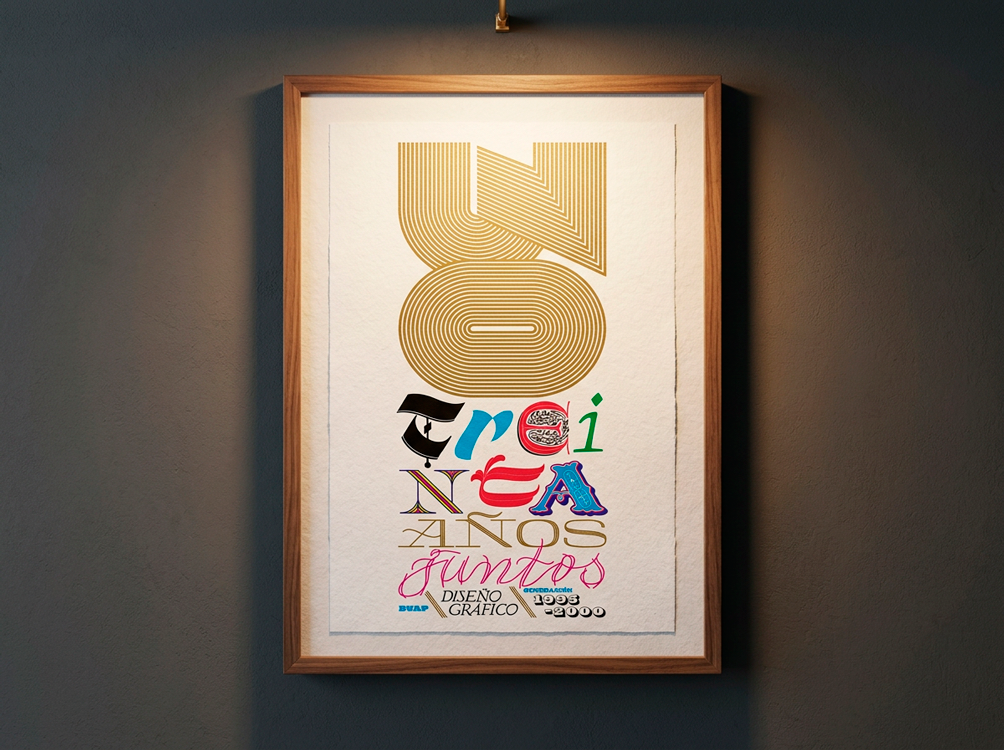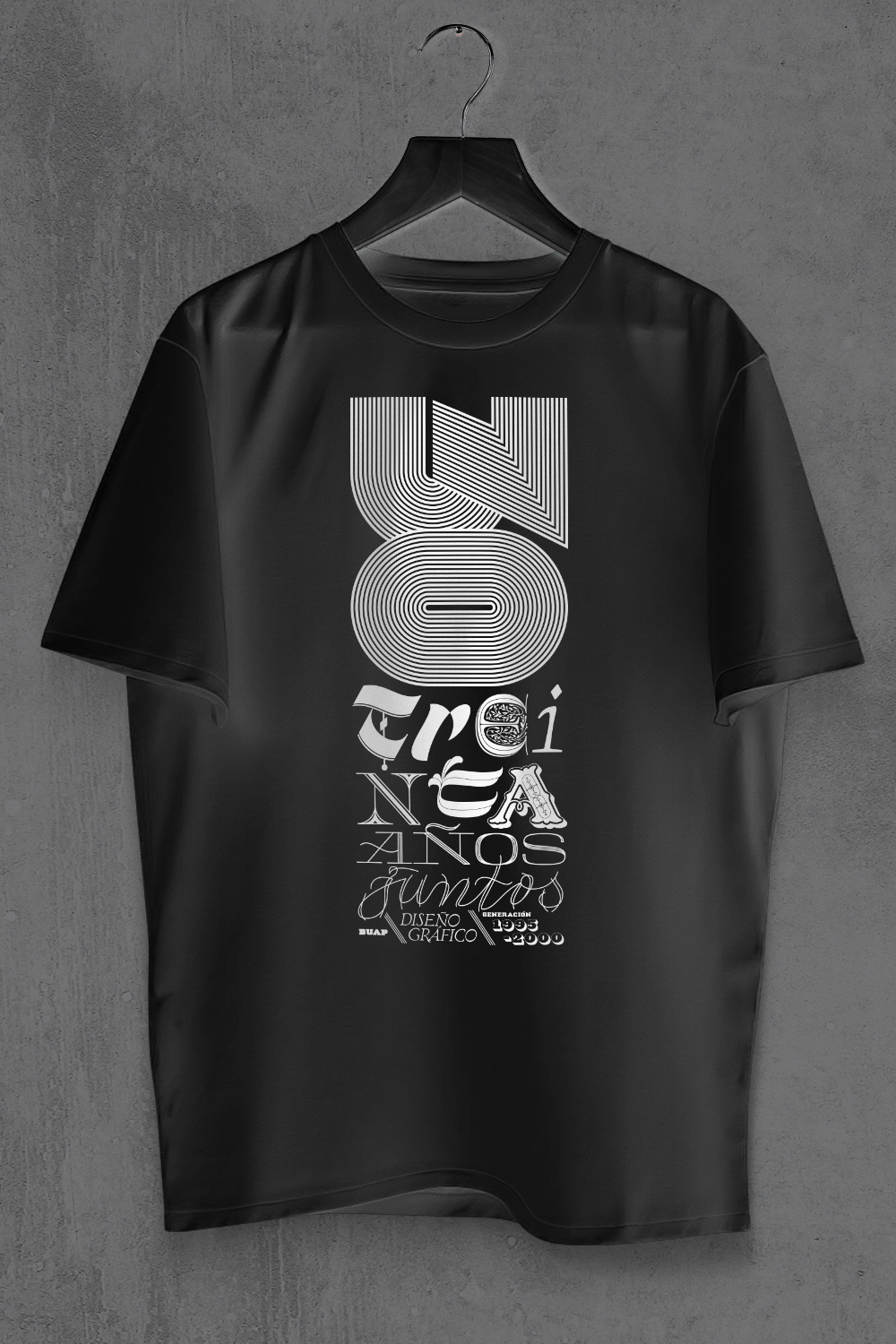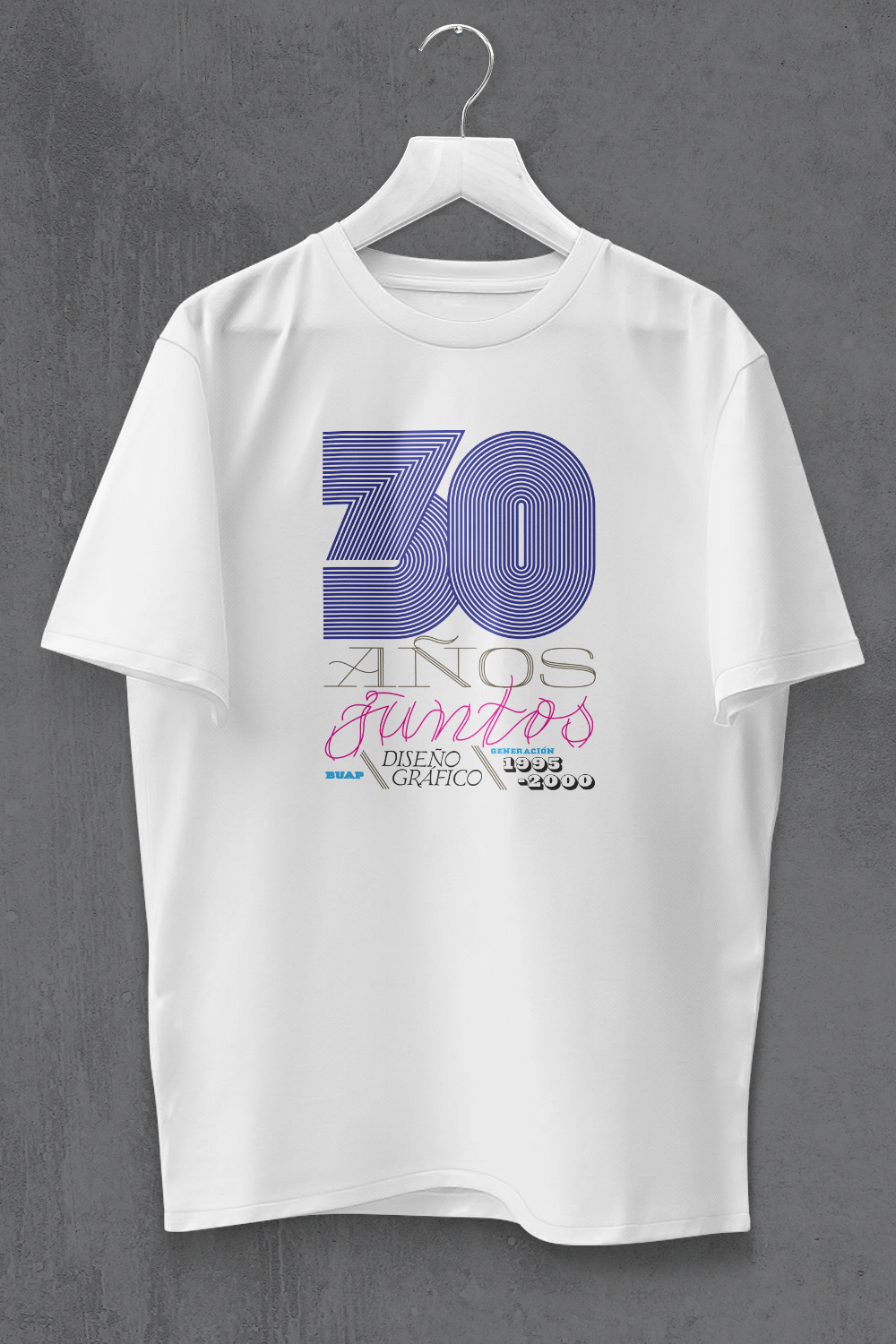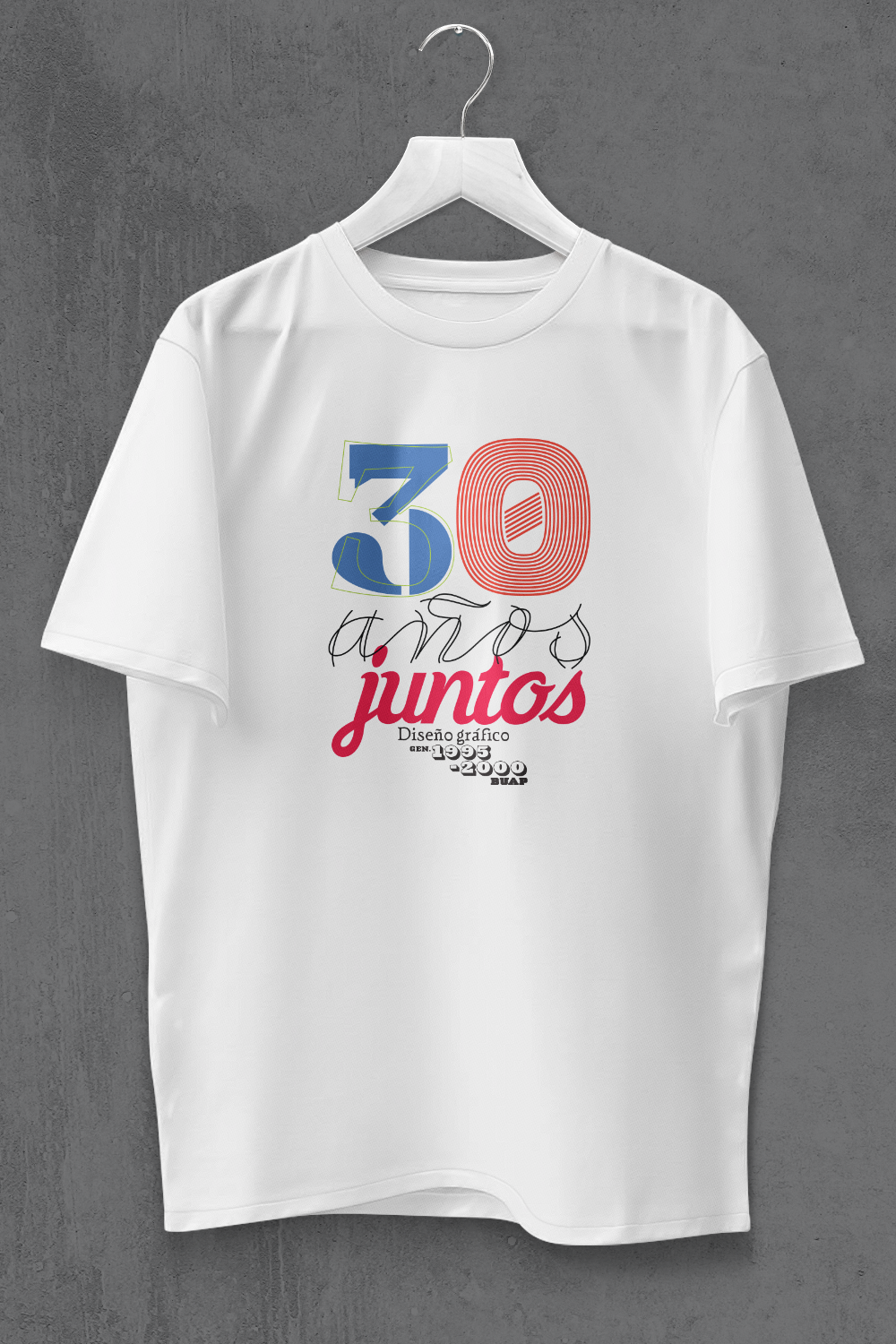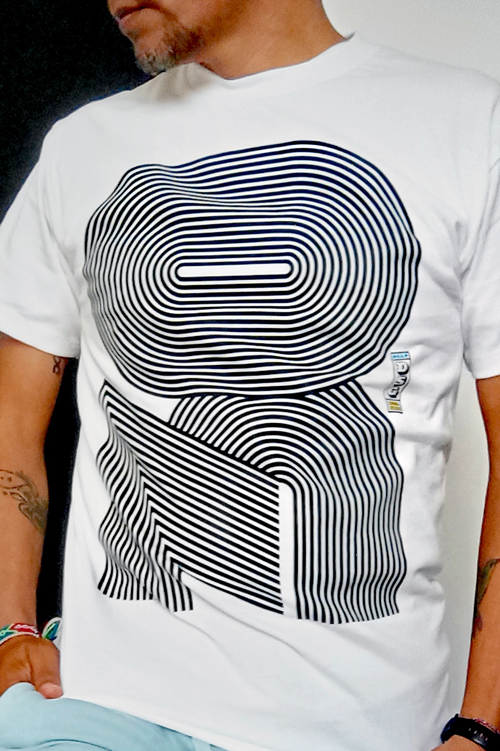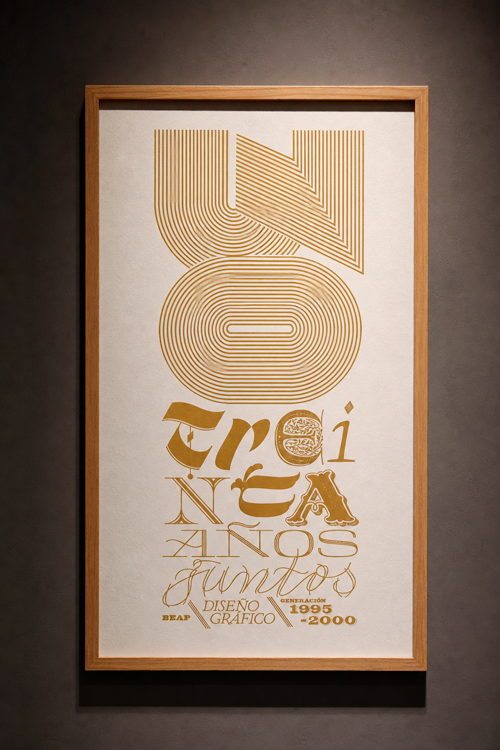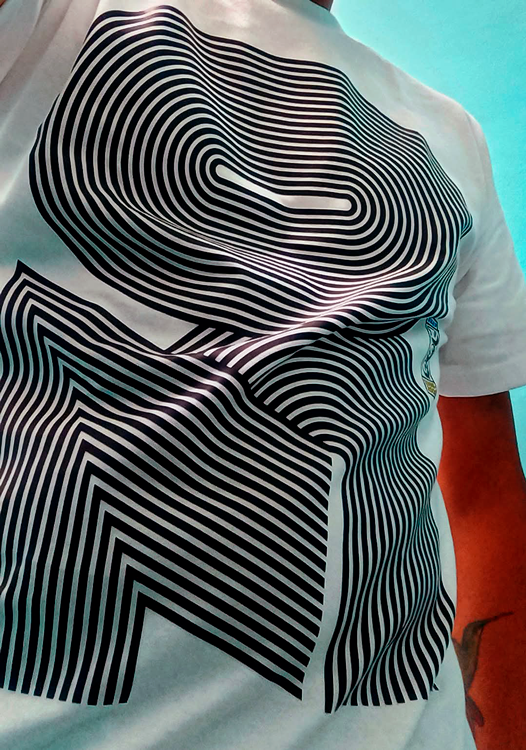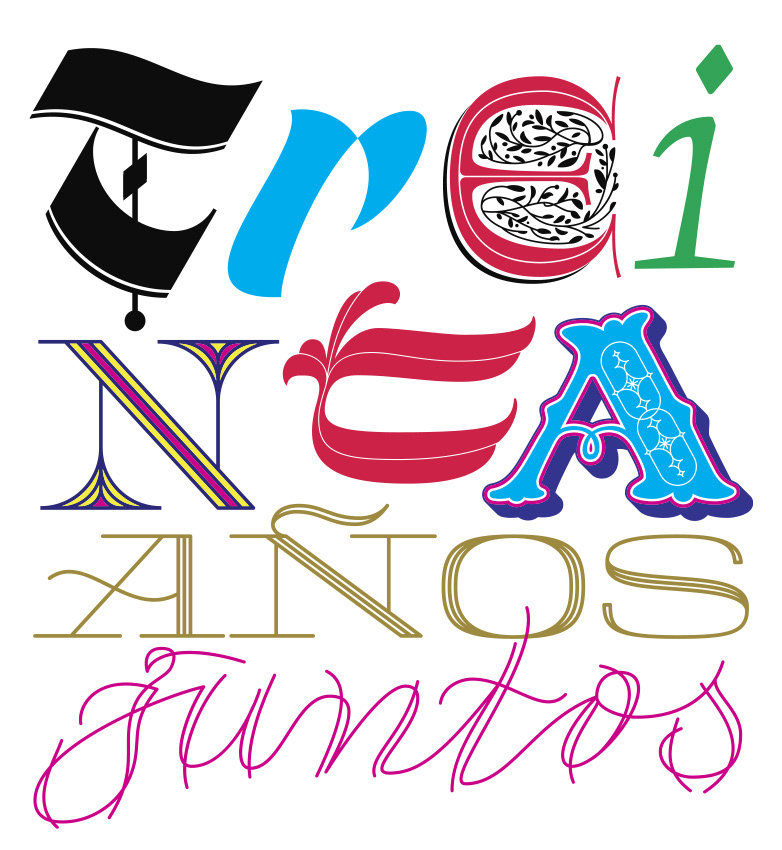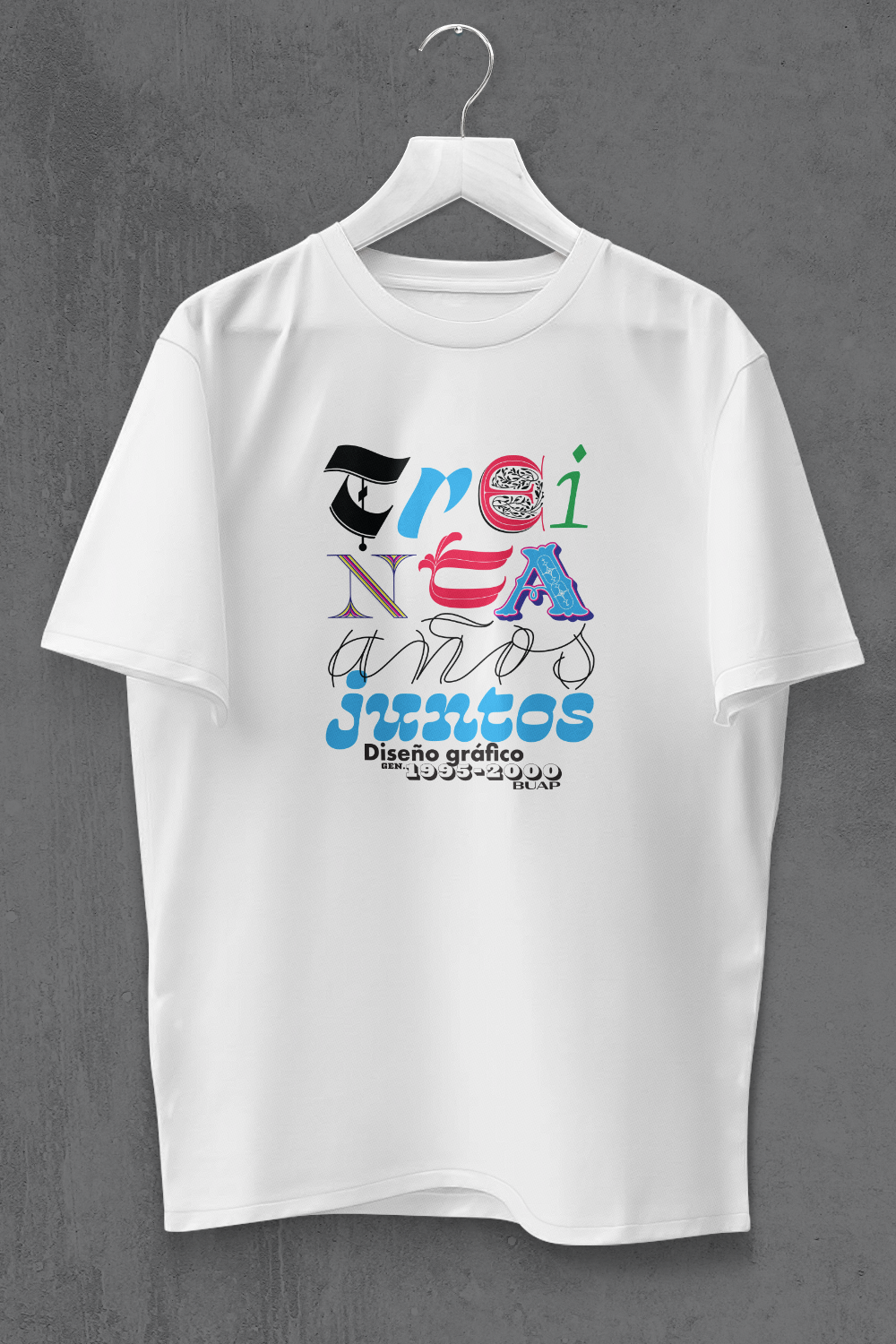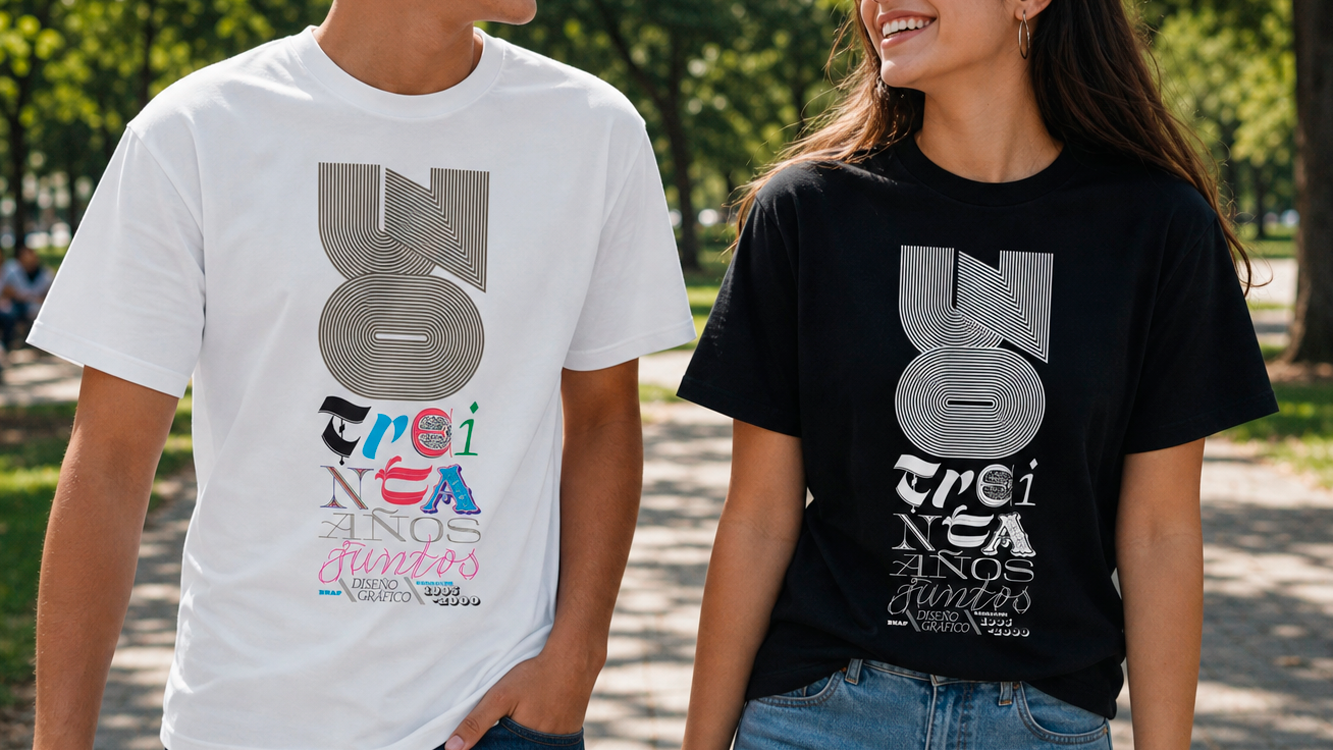
30 años juntos
Logo design y aplicaciones
Logotipo diseñado más otros elementos y variantes que celebra 30 años de generación académica 1995-2000 de la Licenciatura en Diseño Gráfico de la Benemérita Universidad Autónoma de Puebla. Diseñe diversos elementos tipográficos y de rotulación personalizados, enriqueciendo la diversidad y el estudio del lenguaje gráfico a uno muy llamativo y que hace un juego junto a otras versiones que también se exploraron.
Además, he creado y producido otros artículos como ropa, tazas y productos impresos.